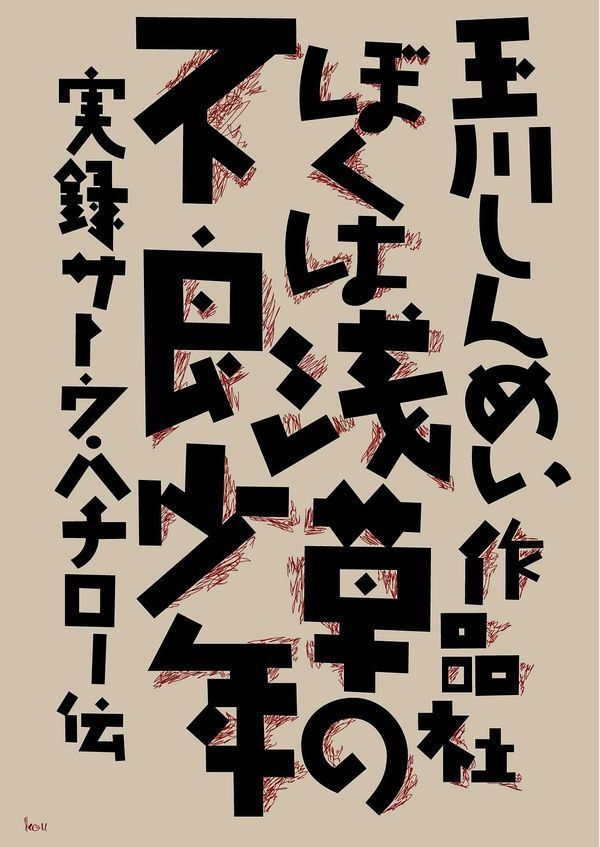
日本设计师平野甲贺(Hirano Kouga)1938年生于首尔,他在日本图书装帧界影响甚广,设计了多达7000册的书籍。
平野甲贺善于用手绘的方式来设计独特字体,并运用到诸多领域的设计作品,拥有自己独特的设计风格。本着“字体必须像空气一样,可以放心地呼吸”的初心,平野先生的文意加字形设计,非常有可看性。
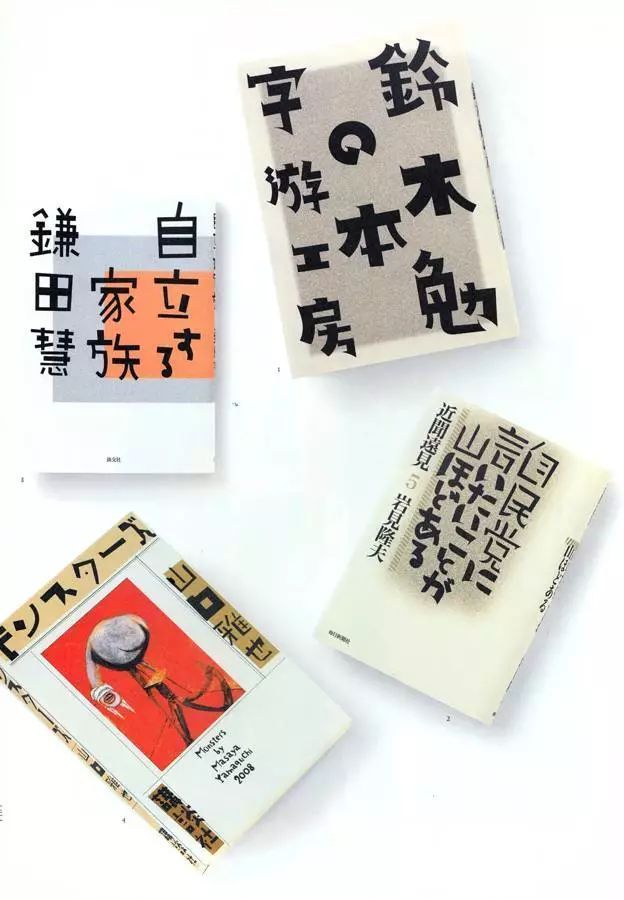
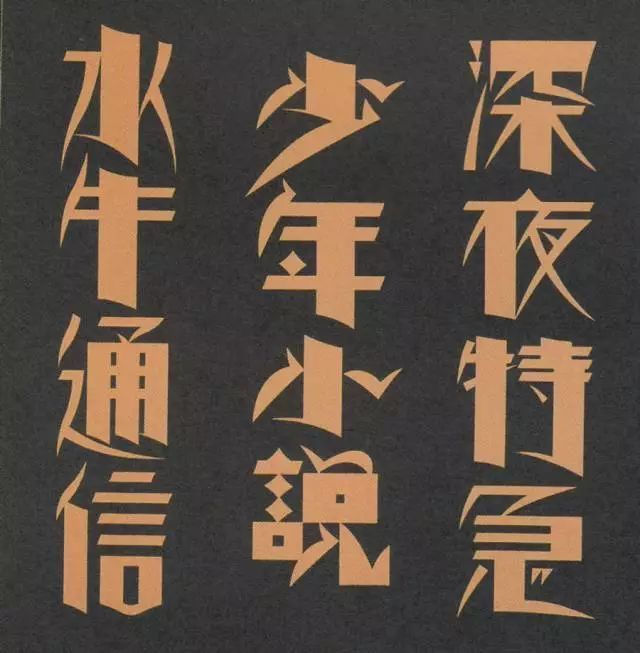
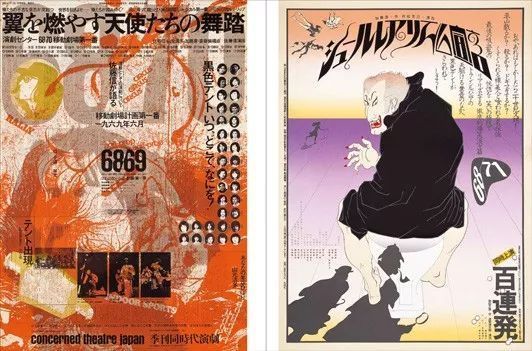
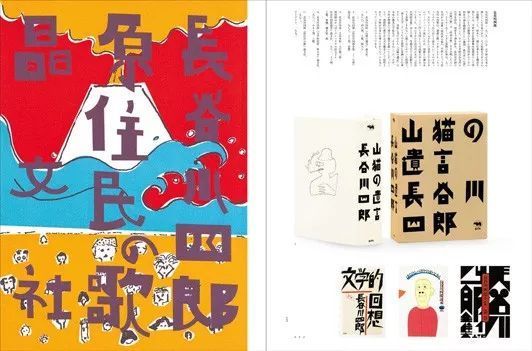
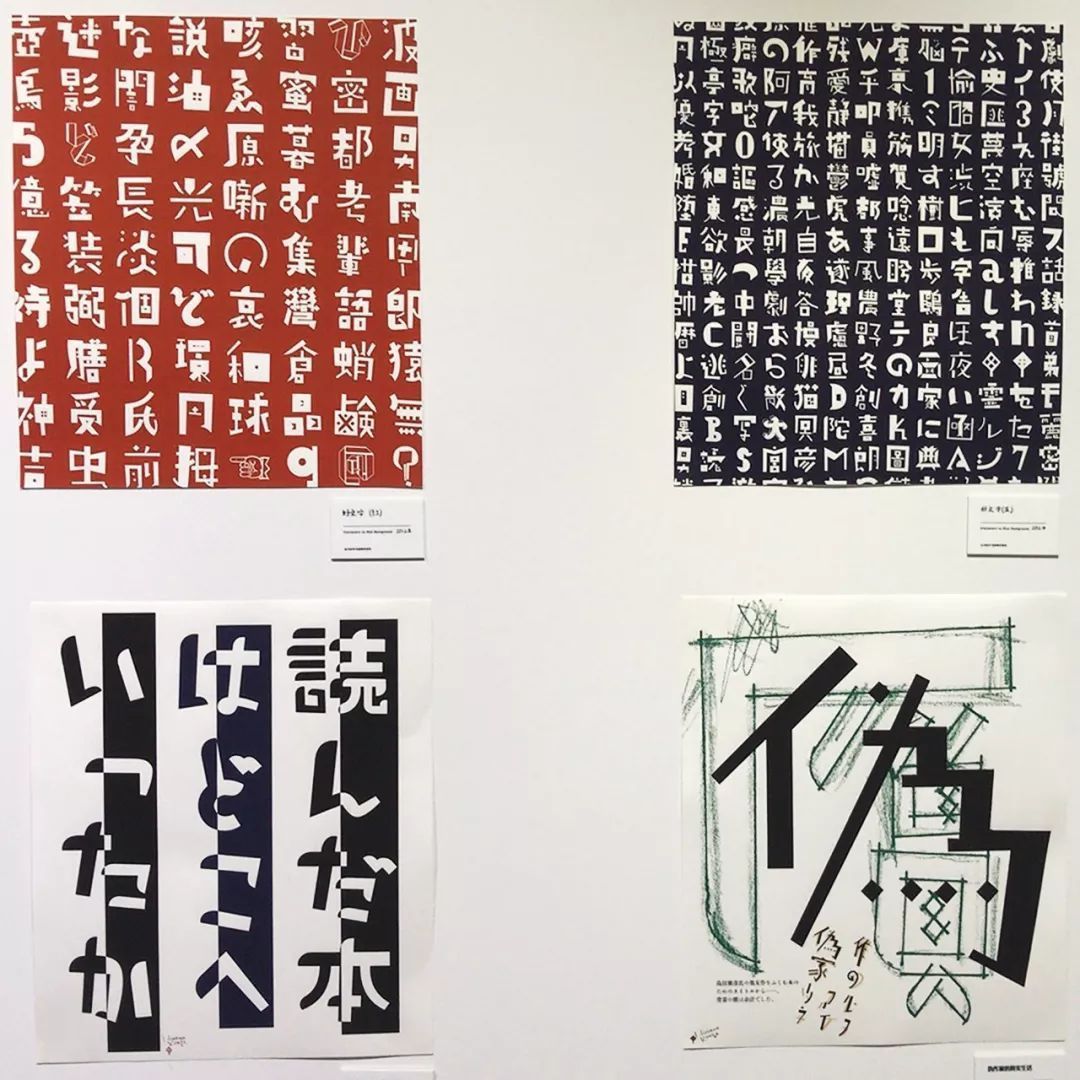
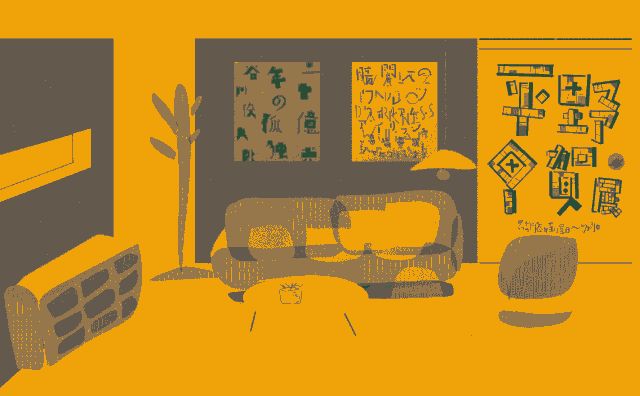
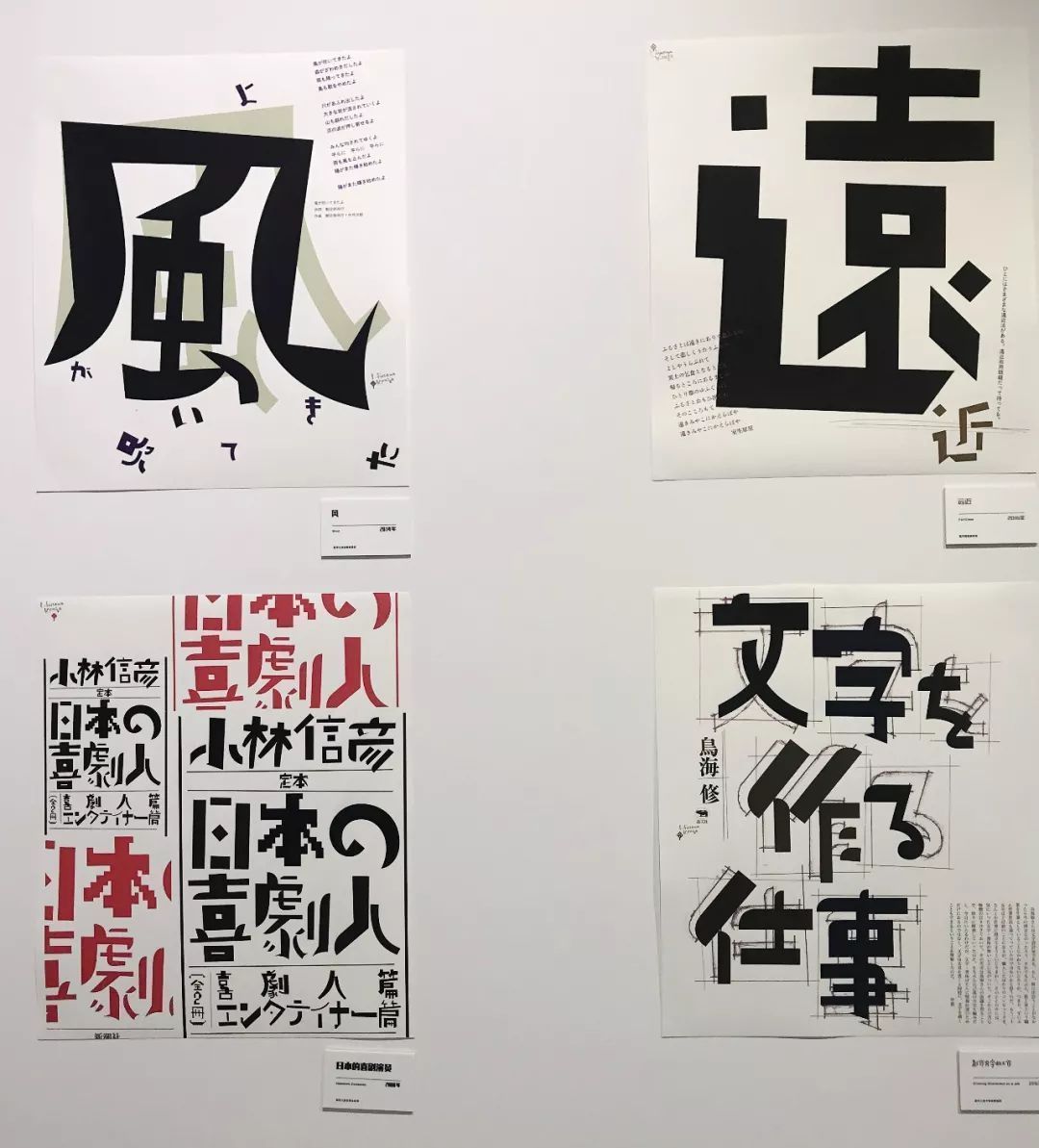
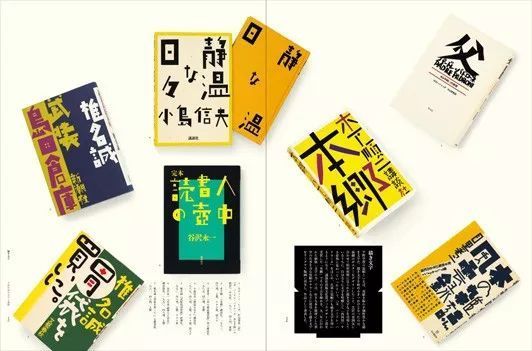
关于平野甲贺(Hirano Kouga)
1938年
出生于首尔。
1957年
进入武藏野美术大学。
1960年
在日本宣传美术会上,以《在看之前便跳》(大江健三郎的小说)的书籍装帧设计获得了特选奖。毕业后进入日本高岛屋公司,之后作为独立设计师。
1964年到1992年
近30年的时间里,他独自包揽株式会社晶文社的全部书籍装帧设计,迄今为止经手的设计已近7000本。他大量使用“手绘文字”。
1960年代
他与晶文社的编辑,挚友津野海太郎先生一起加入以先锋戏剧著称的日本“黑帐篷”剧团,连续创作出《鼠小僧次郎吉》(1971年)和《舒尔雷尔主义宣言》(1973)等多幅具有话题性的话剧海报。
1973年
他成为由植草甚一创刊的《WonderLand》杂志停刊后又全新出版的《宝岛》杂志的艺术总监,以特立独行方式呈现。
1984年
他加入了由高桥悠治等人创建的“水牛乐团”,并积极投入亚洲公众文化交流的“水牛”的活动。同年,他的作品之一木下顺二撰写的《本郷》书籍装帧设计夺得了讲谈社出版文化奖的设计大奖。
1992年
以后,他陆续在国内外举办将书籍装帧设计再现成版画的个人展览“文字的力量”。
2005年
在神乐坂设立小剧场“映画馆易瓦特”。
2011年
转至西神田,并成立了“易瓦特工作室”,直到2013年。
2014年
偕同夫人移居小豆岛,过着深居简出的生活,继续创作。
2018年
1月到3月,在东京银座ggg画廊举办个人展